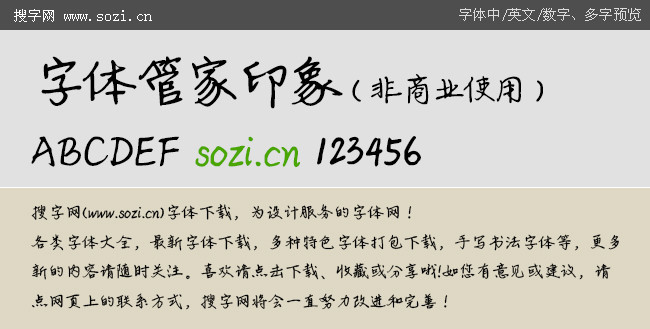
字體管家印象(非商用版)
搜字網(wǎng)給大家提供一款字體管家印象(非商用版)中文字體下載,該字體是一款手寫中文字體,這款字體字形簡潔方正,干凈利落,適合包裝設(shè)計、書裝設(shè)計、海報設(shè)計等應(yīng)用(此字體為個人非商用版,商用可以聯(lián)系QQ:1006760504)。